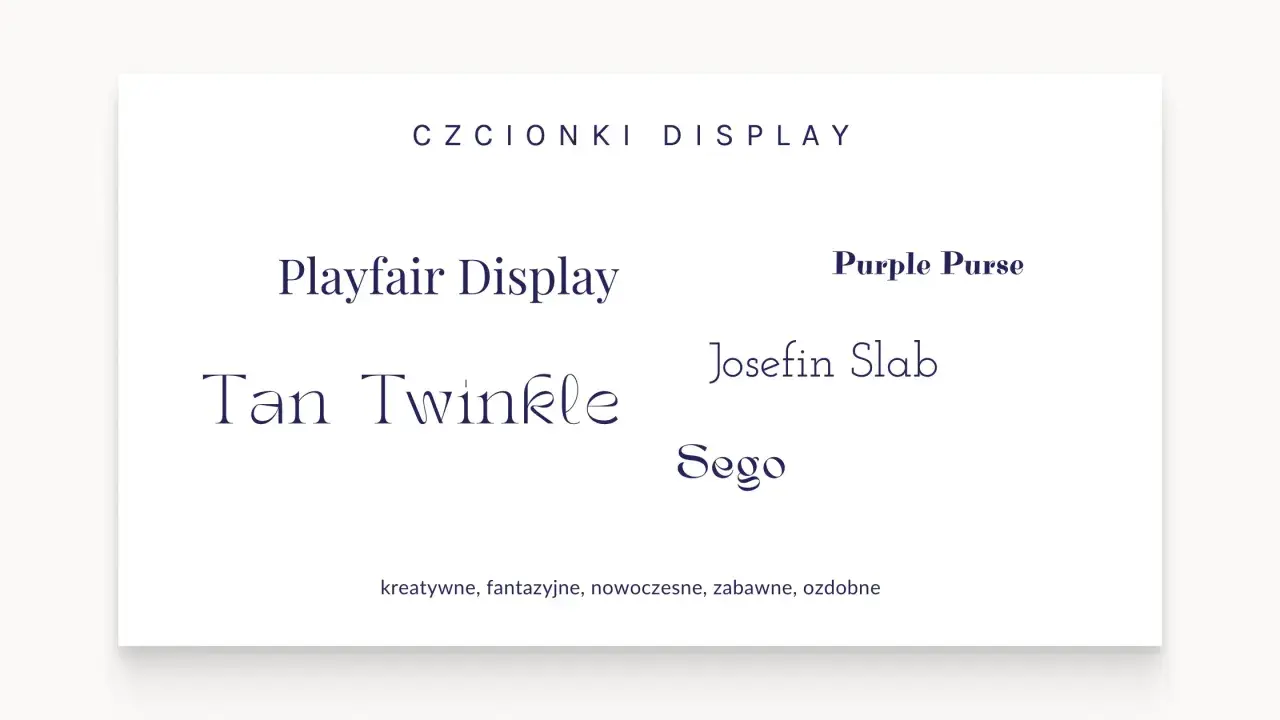
Czytelność kroju pisma nie zależy wyłącznie od tego, czy font jest szeryfowy, czy bezszeryfowy. W praktyce liczą się też rozmiar, interlinia, kontrast, szerokość wiersza i to, czy tekst ma działać na ekranie, w druku czy na szyldzie. Jeśli chcesz wybrać najbardziej czytelną czcionkę do konkretnego zastosowania, musisz patrzeć na cały układ, a nie tylko na nazwę fontu.
Wybór czytelnego kroju zaczyna się od prostoty, a kończy na dobrym składzie
- Na ekranie najczęściej wygrywa prosty sans-serif o otwartych kształtach liter.
- W dokumencie i na stronie bezpieczny punkt startu to 16 px i interlinia 1,5.
- W WCAG dla zwykłego tekstu próg kontrastu wynosi 4,5:1.
- Za czytelność mocno odpowiada też szerokość wiersza, najlepiej około 45-75 znaków.
- Font displayowy może wyglądać efektownie, ale w dłuższym tekście szybko męczy wzrok.
- W materiałach dla lokalnej firmy najważniejsze jest to, by klient odczytał komunikat w kilka sekund.
Nie ma jednego fontu, który wygra wszędzie
Najkrótsza uczciwa odpowiedź brzmi: nie istnieje jedna uniwersalna, najbardziej czytelna czcionka. To, co działa w aplikacji mobilnej, nie zawsze sprawdzi się na ulotce, a to, co wygląda elegancko w logotypie, może być męczące w dłuższym akapicie.
W swojej pracy zaczynam więc od pytania nie o sam krój, ale o scenariusz. Czy tekst będzie czytany w biegu, na małym ekranie, z daleka, czy przez kilka minut w spokojnym tempie? Odpowiedź zmienia wszystko. Dla strony internetowej najlepiej działa prosty, neutralny font. Dla materiału drukowanego można pozwolić sobie na większy charakter, ale nadal bez ozdobników, które utrudniają odczyt.To ważne także z perspektywy marketingu lokalnego: klient zwykle nie analizuje typografii, tylko skanuje treść i szuka konkretu. Jeśli nagłówek, numer telefonu albo cena są czytelne od razu, projekt już spełnia swoją rolę. Dalej decydują szczegóły składu, więc przechodzę do nich bez zbędnej teorii.
Co naprawdę decyduje o czytelności
Sam wybór kroju to dopiero początek. Odbiór tekstu mocno zmieniają parametry, które wielu osobom wydają się drugorzędne, a w praktyce robią większą różnicę niż nazwa fontu.
| Czynnik | Co pomaga | Co psuje odbiór |
|---|---|---|
| Rozmiar | Minimum 16 px w sieci, większy tekst dla osób starszych i na telefonach | Mały, „oszczędny” zapis, który wygląda nowocześnie, ale męczy po 2 sekundach |
| Interlinia | Około 1,5 wysokości tekstu | Zbyt ciasne wersy, przez które oko gubi początek kolejnej linii |
| Kontrast | Wyraźna różnica między tekstem a tłem | Jasnoszary tekst na białym tle albo napis na zdjęciu bez zabezpieczenia |
| Długość wiersza | Około 45-75 znaków w dłuższym tekście | Przesadnie długie linie, po których wzrok „płynie” zbyt daleko |
| Grubość kreski | Regular, medium lub semibold | Light i ultra light w małym rozmiarze |
| Kształt liter | Otwarte wnętrza liter, wyraźne różnice między podobnymi znakami | Wąskie, sklejone formy i małe odstępy między znakami |
Warto też pamiętać o x-height, czyli wysokości małych liter bez ogonków i wydłużeń. Im wyższy x-height względem wielkich liter, tym litery zwykle są łatwiejsze do rozróżnienia na ekranie. To jeden z powodów, dla których niektóre proste fonty wyglądają po prostu czyściej od innych. Na tym tle łatwiej zrozumieć, które rodziny krojów faktycznie wygrywają w praktyce.
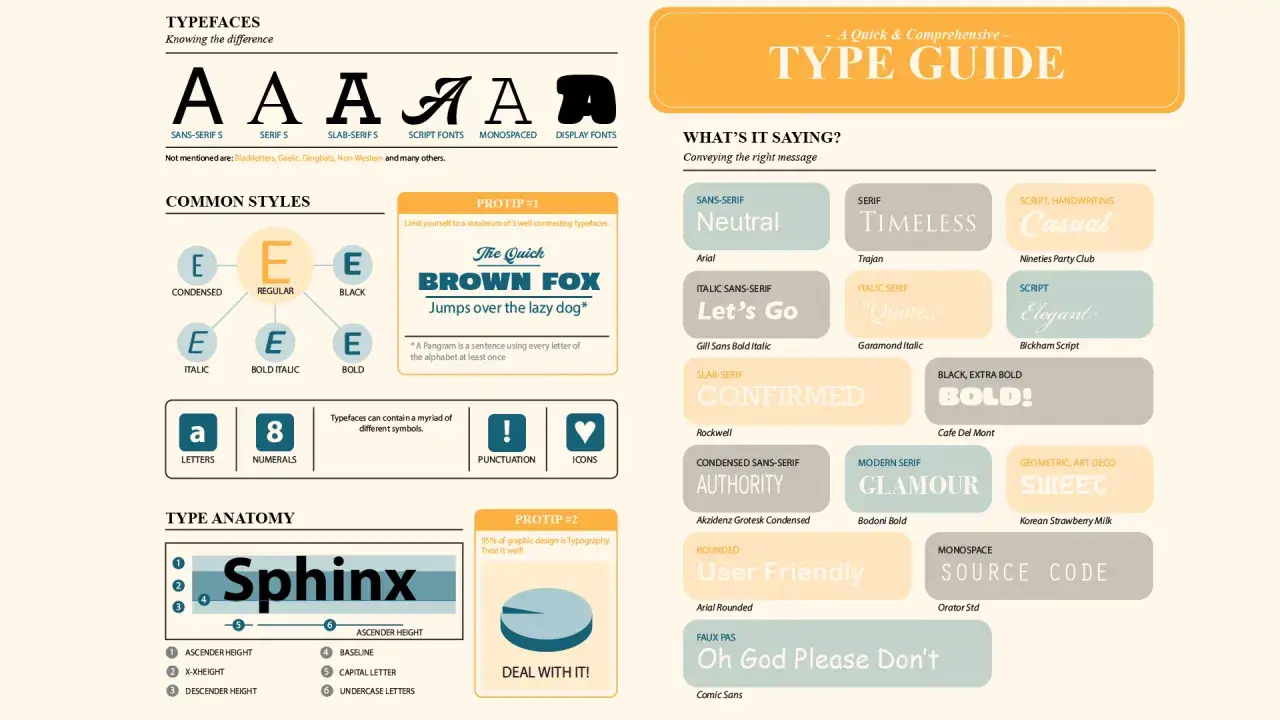
Jakie kroje najczęściej wygrywają w praktyce
Jeśli potrzebujesz bezpiecznego wyboru do internetu, najczęściej stawiam na proste sans-serify z dużym x-height i otwartymi kształtami. HHS/ODPHP w swoich wytycznych zaleca co najmniej 16 px i właśnie taki, popularny kierunek: prosty, znany użytkownikowi, bez ozdobników, które rozbijają rytm czytania.
| Rodzina kroju | Kiedy działa najlepiej | Dlaczego bywa czytelna | Na co uważać |
|---|---|---|---|
| Humanistyczny sans-serif | Strony usługowe, treści mobilne, interfejsy | Ma otwarte wnętrza liter i naturalny rytm | Nie wybieraj zbyt cienkiej wersji |
| Neutralny sans-serif | Nagłówki, formularze, krótkie informacje | Jest prosty i przewidywalny | W dłuższym tekście może wyglądać zbyt „technicznie” |
| Serif o dobrej konstrukcji | Artykuły drukowane, katalogi, dłuższe teksty w spokojnym układzie | Pomaga prowadzić oko po linii i daje klasyczny charakter | W małym rozmiarze i na słabym ekranie traci przewagę |
| Display | Logotypy, hasła, pojedyncze wyróżnienia | Buduje nastrój i odróżnia markę | Nie używaj go w akapitach |
| Condensed | Ograniczona przestrzeń, np. plakaty | Upycha dużo treści w małym miejscu | Często obniża czytelność, zwłaszcza przy dłuższych zdaniach |
W praktyce najczęściej wracam do takich krojów jak Verdana, Open Sans, Source Sans, Roboto, Calibri czy Lato. To nie dlatego, że są „najpiękniejsze”, tylko dlatego, że dobrze znoszą małe rozmiary, mobile i szybkie skanowanie treści. Z kolei Georgia bywa bardzo dobra w dłuższym druku, ale nie traktowałbym jej jako automatycznie lepszej od sans-serifu w sieci. W typografii nie ma jednego zwycięzcy, jest dopasowanie do medium.
Ta różnica ma znaczenie również dla lokalnych marek, które chcą wyglądać profesjonalnie bez przesadnej stylizacji. Następny krok to przełożenie tych zasad na konkretny kanał komunikacji.
Jeśli chcesz zacząć od jednego sprawdzonego kierunku, wybierz prosty sans-serif, ustaw rozsądny rozmiar i zadbaj o kontrast, a dopiero potem dopracuj charakter projektu. To zwykle daje lepszy efekt niż szukanie idealnej czcionki przez samą nazwę. W praktyce właśnie tak buduje się tekst, który jest naprawdę wygodny do czytania.